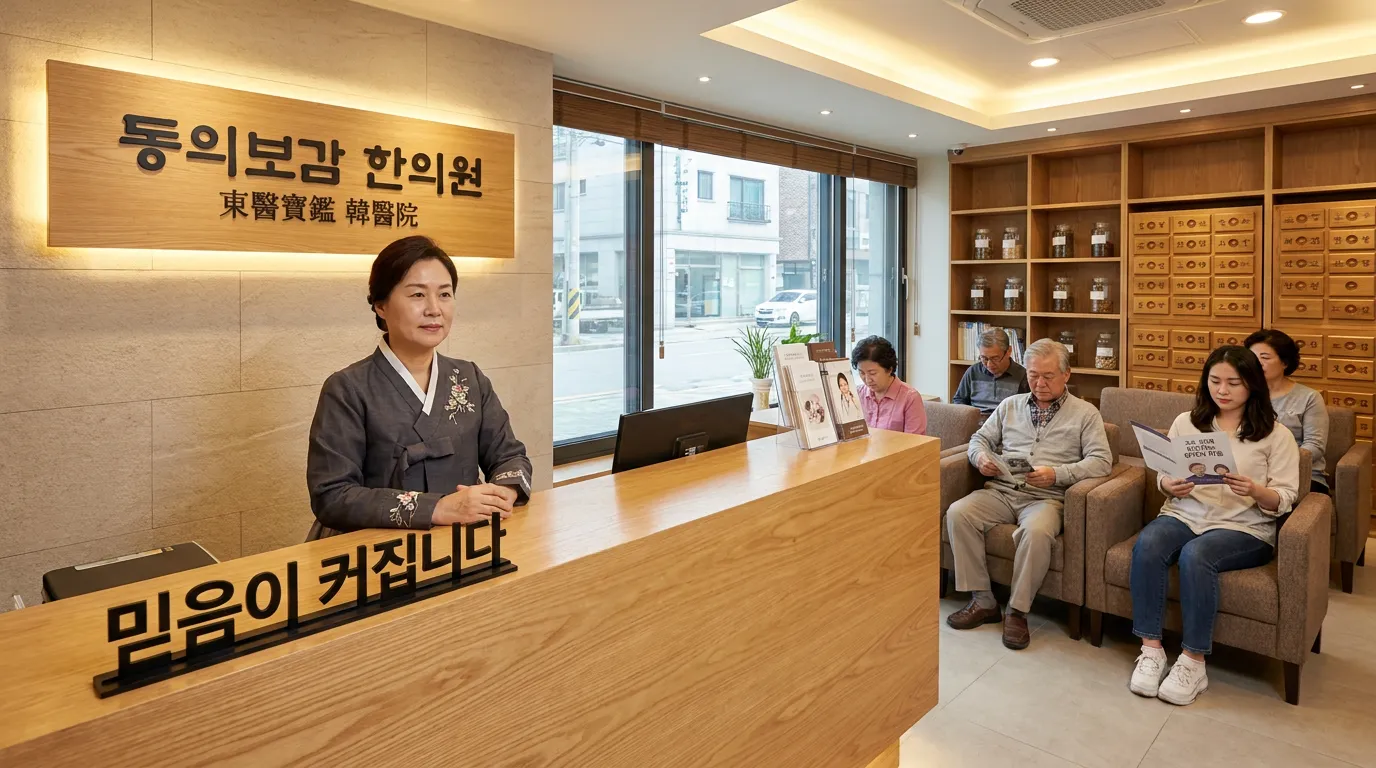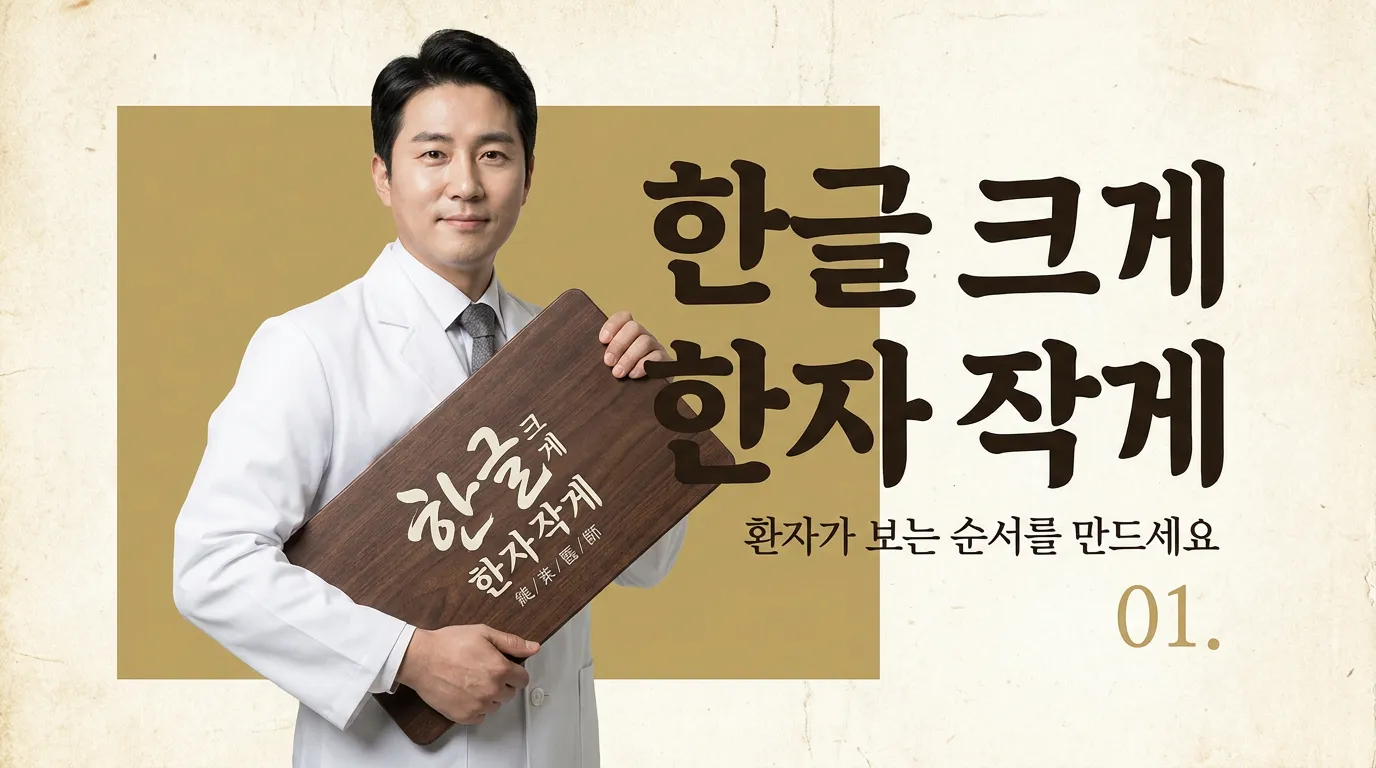
한의원 로고 폰트, 한글은 크게 한자는 작게 써야 믿음이 커집니다
한의원 로고 폰트 선택에서 한글·한자 비율, 획 굵기, 명조체 사용 기준까지 실제 개원 브랜딩 관점으로 정리했습니다.
환자는 ‘淸’자를 읽고 들어오는 게 아니라, 3초 안에 ‘여기 내 몸 맡겨도 되나’를 판단합니다.
한자는 많이 넣을수록 더 전문적으로 보일까요?
원장님들이 가장 자주 하는 실수가 있습니다. 한의원 로고에 한자를 크게 넣고, 한글은 설명처럼 작게 붙이는 방식입니다. 멋은 있어 보이는데 환자 입장에선 먼저 읽히지 않습니다.
저라면 반대로 갑니다. 한글 이름을 주인공으로 두고, 한자는 인장처럼 작게 씁니다. 예를 들면 ‘온유한의원’이라면 ‘온유’를 먼저 보이게 하고, 옆이나 아래에 溫柔를 20~35% 크기로 둡니다. 한자는 읽으라고 두는 글자가 아니라, 결을 보태는 장치입니다.
보건복지부 의료광고 가이드라인에서도 의료기관 명칭과 진료과목을 함께 표시할 때 글자 크기 기준을 따로 둡니다. 결국 의료 쪽 시각물은 ‘크기 차이’가 환자 오인을 만들 수 있다는 뜻이에요. 로고에서도 같은 원리로 봐야 합니다.
명조체를 쓰면 무조건 오래된 한의원처럼 보일까요?
아닙니다. 문제는 명조체가 아니라 획 끝의 감정입니다. 붓글씨 느낌이 과하면 ‘전통’보다 ‘낡음’이 먼저 옵니다. 반대로 너무 둥근 고딕을 쓰면 한의원보다 건강식품 브랜드처럼 보일 수 있고요.
제가 현장에서 잡는 기준은 이렇습니다. 한글은 획 대비가 약한 현대 명조나 단단한 세리프 계열로 잡고, 한자는 더 얇게 갑니다. 한글과 한자가 똑같이 힘주면 서로 싸웁니다. 환자가 보는 순서가 흐려져요.
특히 ‘ㅁ, ㅇ, ㅎ’이 많은 이름은 둥글게 만들수록 부드러워지지만, 너무 풀면 진료의 깊이가 사라집니다. 그래서 한의원 로고 폰트는 예쁜 글씨 찾기가 아니라, 부드러움과 단단함의 비율을 정하는 일에 가깝습니다.
한글 로고 옆에 작은 한자 인장이 배치된 브랜드 시안
한글·한자 조합은 어디까지 줄여야 할까요?
로고 안에 뜻을 다 설명하려고 하면 실패합니다. ‘바를 정 正’, ‘편안할 안 安’, ‘맑을 청 淸’ 같은 한자를 전부 보여주고 싶어도, 로고는 사전이 아닙니다.
이렇게 하세요. 한자는 1~2자만 남기고, 나머지 의미는 컬러와 여백으로 넘기면 됩니다. 예를 들어 회복을 말하고 싶다면 초록을 크게 쓰는 대신 먹색에 낮은 채도의 청록을 한 끗만 섞는 편이 더 오래 갑니다. 한의원은 튀는 순간보다 오래 남는 쪽이 유리합니다.
디자인 연구에서도 타이포그래피는 단순한 장식이 아니라 선호도, 구매의도, 추천의도 같은 판단에 영향을 주는 시각 요인으로 다뤄집니다. 의료기관이라면 구매보다 더 예민합니다. 환자는 치료 전부터 글자 모양으로 태도를 읽습니다.
네이버 지도 썸네일에서도 살아남나요?
좋은 한의원 로고 폰트는 큰 간판에서만 예쁘면 안 됩니다. 네이버 지도, 카카오맵, 예약 문자, 약봉투, 명함에서 같이 버텨야 합니다. 여기서 한자가 너무 얇으면 사라지고, 한글이 너무 장식적이면 뭉개집니다.
마크에서 한의원 로고를 잡을 때도 첫 시안부터 작은 화면 테스트를 같이 봅니다. 멀리서 보는 간판보다, 요즘 환자는 지도 검색 화면에서 먼저 만나니까요. 이때 한글 이름이 1초 안에 읽히고, 한자가 분위기만 보태면 성공입니다.
지금 당장 할 행동 한 줄: 한의원 이름을 휴대폰 화면 3cm 크기로 줄여보고, 한글이 먼저 읽히지 않으면 폰트부터 다시 보세요. 작품 둘러보기에서 한글·한자 조합 사례를 비교해보면 감이 더 빨리 옵니다.